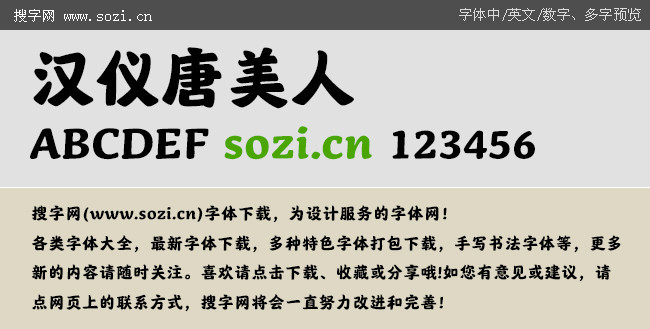
漢儀唐美人
搜字網(wǎng)給大家提供一款漢儀唐美人中文字體下載。漢儀唐美人簡是一款適用性非常廣泛的中文字體,該字體線條粗壯有力,筆力勁健挺拔,瘦勁精勻,整體效果非常出色,適合應(yīng)用與藝術(shù)設(shè)計、平面宣傳設(shè)計、網(wǎng)頁設(shè)計、海報設(shè)計等應(yīng)用。(本字體為個人非商用版,如需要商用請聯(lián)系漢儀公司購買版權(quán))